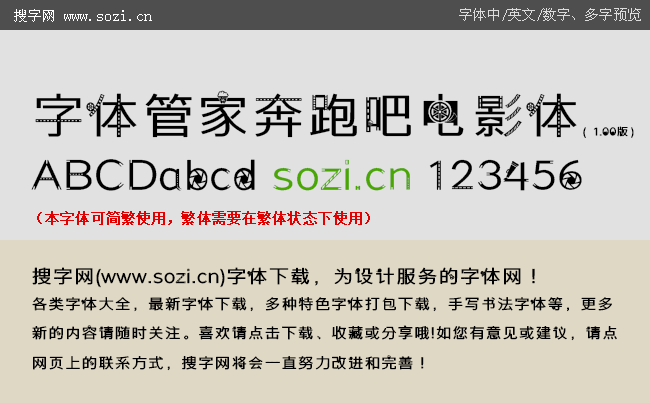
字體管家奔跑吧電影體
搜字網(wǎng)給大家提供一款很有趣的手機(jī)中文字體下載。字體名字叫字體管家奔跑吧電影體,這款手機(jī)字體是以黑體字體為原形。在字體的個(gè)別筆畫(huà)上裝飾了電影膠片的圖案,使字體變得有趣。特別適合喜歡手機(jī)字體個(gè)性一些的朋友在手機(jī)上安裝使用。